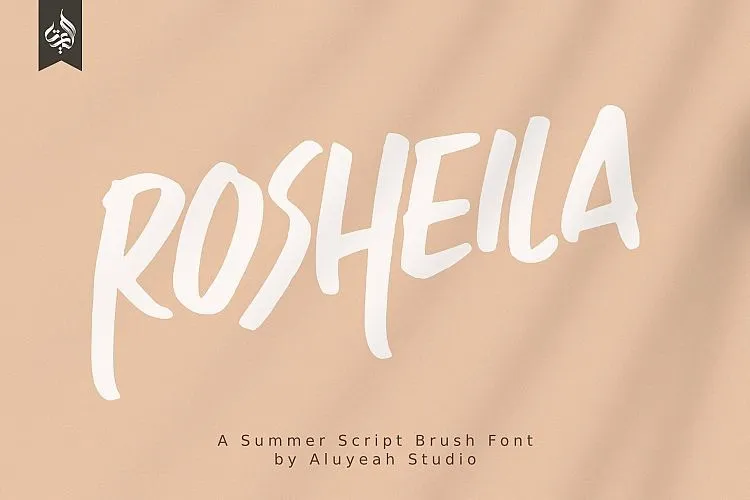
Rosheila Brush Font – Download Grátis
A Rosheila Brush Font é uma fonte criada à base de escrita natural. Ela adota um estilo bold que destaca a sua presença assertiva e atrativa, tornando seu trabalho ainda mais impressionante! Através do Aluyeah Studio, foi projetada para oferecer esse toque vibrante da estação quente, adequado para quem valoriza uma sensação descontraída, casual e livre. Perfeito para criar design belo e autêntico de letra à mão, a Rosheila Brush é uma fonte script brush que vem com 32 alternativas de letras para obter um visual perfeitamente casca-grossa e elegante. Com ela, você pode adicionar um toque vibrante ao seu trabalho, seja em designs pessoais ou corporativos.